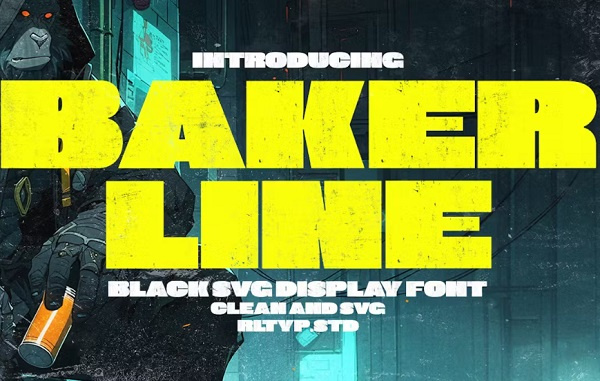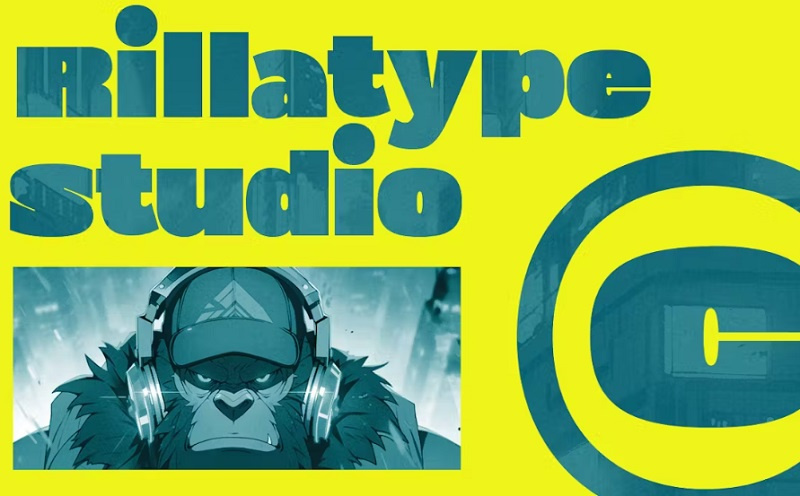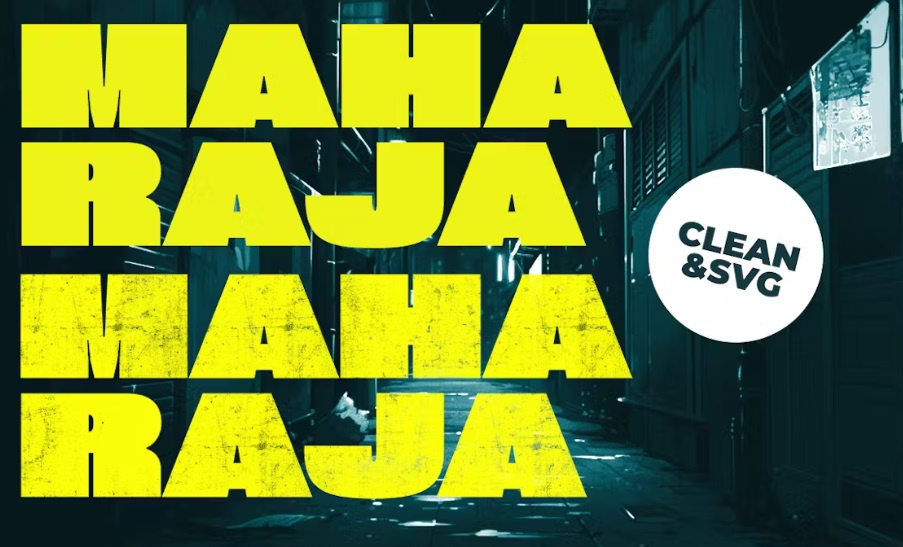
دانلود فونت انگلیسی Bakerline Display
دانلود فونت انگلیسی Bakerline Display. این فونت با وزن بسیار پررنگ موجود است که برای طراحی هایی که به بیان قدرتمند نیاز دارید ایده آل است. برای مشاهده پیش نمایش این فونت انگلیسی و دانلود آن در ادامه مطلب از جی اف ایکس دانلود با ما همراه باشید.
فونت انگلیسی Bakerline Display